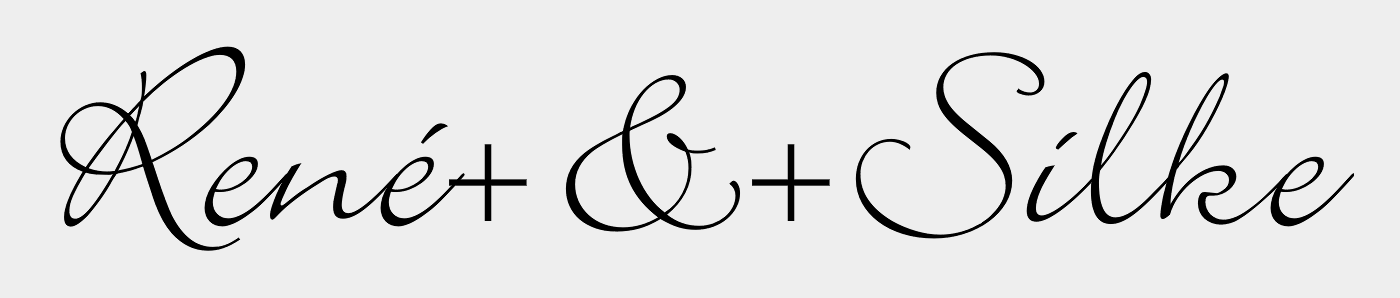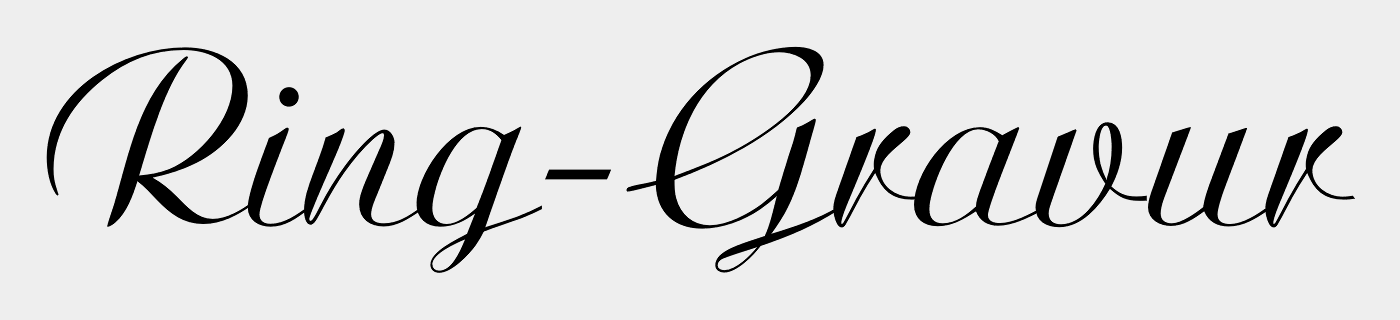
Ehe-Ringe Gravur-Schrift
Das hatte ich früher auch immer so gemacht – bis mich der Graveur mal aufgeklärt hat, dass er die Vektordaten ausdruckt, einscannt und seine Graviermaschine mit dem Bild füttert.
Immerhin! Meiner druckt die Vorlage meist aus und baut sie in Corel Draw »nach«, aber ausschließlich in ASCII (so fallen typografische Apostrophe und Anführungszeichen schon mal weg), ohne jede Silbentrennung, mit komplett anderen Abständen und, wenn in der Vorlage irgendeine Serifenschrift benutzt wurde, immer in Times New Roman.
Unser Graveur hat die PDF auch gedruck und gescannt ... Die scheinen alle nicht so auf der Höhe der Zeit zu sein ... Und der Typ, der für uns nen Siegel graviert hat, hat das scheinbar sogar freihand gemacht :-?
Ich habe Ringe bisher hier bestellt, und
schien für mich immer, dass eher Vektordaten verarbeitet werden. Einmal hatten sie aber leider die Schrift sehr klein gerechnet :-(
Die Al Fresco hat unglaublich viele Glyphen an Bord:
Unter anderem viele "S"
Ja, die habe ich gesehen, echt ein super Schriftsatz!
Aber beim "S" bin ich eigenwillig, in Schreibschrift mit Schnörkel gefällt es mir einfach nicht besonders:-?
Hej sille, hast Du vielleicht irgendwas zur Hand, was uns eine grobe Richtung vorgeben könnte: einen Flyer, eine Website oder ähnliches mit einer Schreibschrift, die Dir sehr gefällt? Es gibt so viele tolle Schreibschriften, dass es müßig wäre die jetzt alle hier aufzuzählen. Außerdem scheint mir das auch im Hornberger Schießen zu enden, oder?
... oder bei den freien die Allura:
Hat aber auch das amerikanische & – man könnte auch + statt dessen setzen :-?
Die is toll! Sowas hab ich gemeint!
Stimmt, ein "+" wäre ne Option.
Vielleicht finde ich aber noch ein passendes aus einer ähnlichen Schriftart, oder ich versuche mich auch selbst mal an einem kleinen "&"
Norbert, für mich persönlich wäre das eindeutig der bisherige Favorit. Sehr schön!
für welche Schrift hast Du Dich denn nun entschieden?
Ich finde, bis auf die Allura sehen die meisten Vorschläge sehr nach Eisdiele und weniger nach Hochzeit aus.
Warum muss es denn bei Eheringen immer etwas sein, was in Richtung geschwungene Handschriftnachahmung geht?
Auf mich wirkt das immer irgendwie "nicht echt" (und meist kitschig) - daher finde ich die Idee mit der eigenen Handschrift richtig Klasse.
Die Idee, die Gravur außen aufzubringen, finde ich auch toll.
Wie sind denn die Erfahrungen, was das Zerkratzen angeht?
Die Idee, die Gravur außen aufzubringen, finde ich auch toll.
Wie sind denn die Erfahrungen, was das Zerkratzen angeht?
Also, mein Ring war ursprünglich außen mattiert und die Schriftgravur geht ziemlich tief hinein. Die Mattierung hat sich mit den Jahren etwas abgeschliffen und ja, das Material (Weißgold) hat außen auch ein paar kleine Gebrauchsspuren angenommen. Aber das stört mich gar nicht. Die Schrift ist nach wie vor der Blickfang auf dem Ring (– wie andere Metalle sich in puncto Kratzer verhalten, kann ich nicht beurteilen).
Also die Goldenen ringe meiner Eltern hatten mal ein Muster auf der Außenseite (wie das aufgebracht war weiß ich nicht). Das Muster kenne Inhaber nur aus Erzählungen, denn nach 25 Jahren sind die Ringe einfach völlig glatt außen.
Mein Ringe (besser: unsere Ringe) sind außen matt aber haben schon viele Gebrauchspuren (nach nichtmal einem Jahr). Die Gravur ist aus der Trajan, weil ich die kalligrafischen/handschriftlichen auch nicht gut finde, v.a. nicht in so kleinen Größen. Außerdem passt die Trajan deutlich besser zu unserem Spruch: „Actio est reactio“. Mehr steht nicht drin, unsere Namen und das Datum können wir uns merken :-P
vor 14 Minuten schrieb TobiW:
Mehr steht nicht drin, unsere Namen und das Datum können wir uns merken :-P
Erinnert mich an den Autoaufkleber:
Ich brauche keine Namenaufkleber, ich kann mir die Namen meiner Kinder merken!
:lol:
»Da ich die Ringe ausschließlich für den persönlichen Gebrauch für eben diese eine Frau benötige, würde ich kostenloses Gold bevorzugen.«
– Trotzdem gute Wünsche für die gemeinsame Zeit.
Na, dann kann ich doch nur Open-Source-Gold empfehlen. Allerdings ist das sehr schlecht dokumentiert, und man muss eine Reise dort hin einplanen, wo das Open-Source-Gold noch liegt. Hacke, Spaten und ne Goldwäscherpfanne ist unabdingbares Zubehör.
Und dann mal auf die Bilder schauen und man bekommt ganz viele mehr oder weniger seriöse Quellen ... Wer weiter suchen will: Script 820 hatte Dateinamen ca820 wie Calligraphic ... Mehr Informationen gibt mein Archiv nicht her.
PS: Die Arioso SM ist immer noch auf meinen Rechnern als Erbe aus der OS/2-Zeit installiert. Ein weiteres Erbe ist die Chevara, eine Chevalier AKA Maurice.